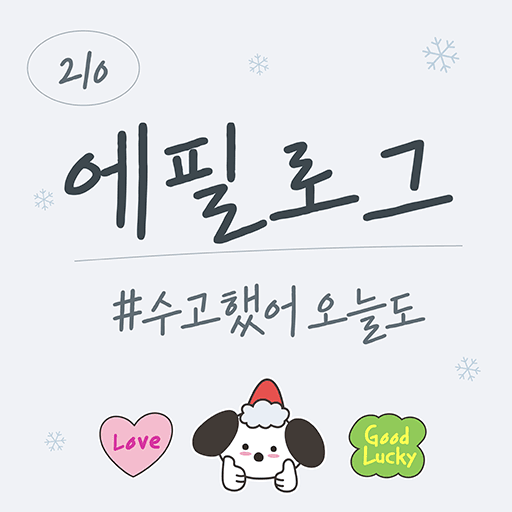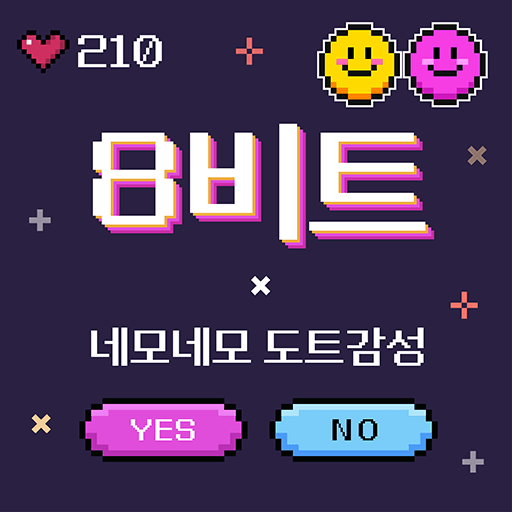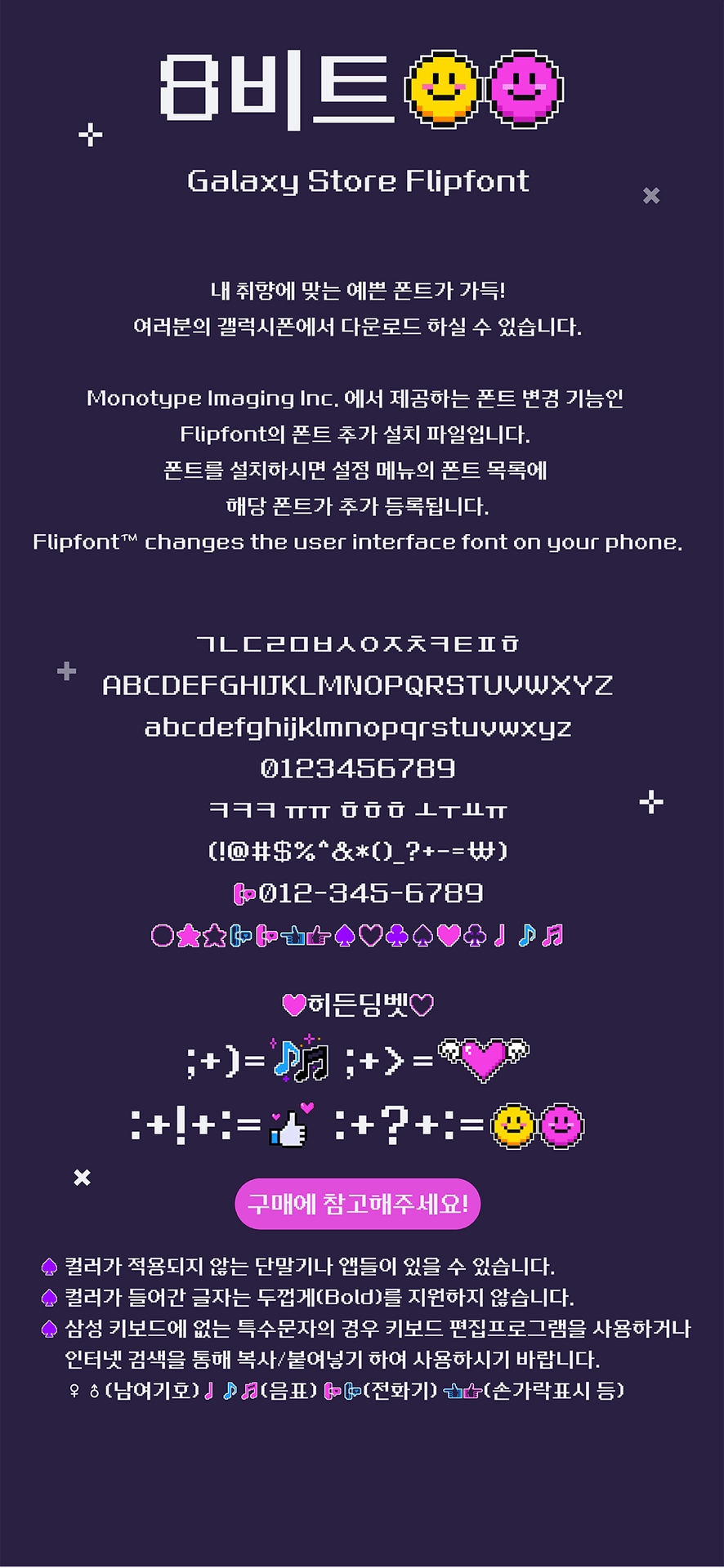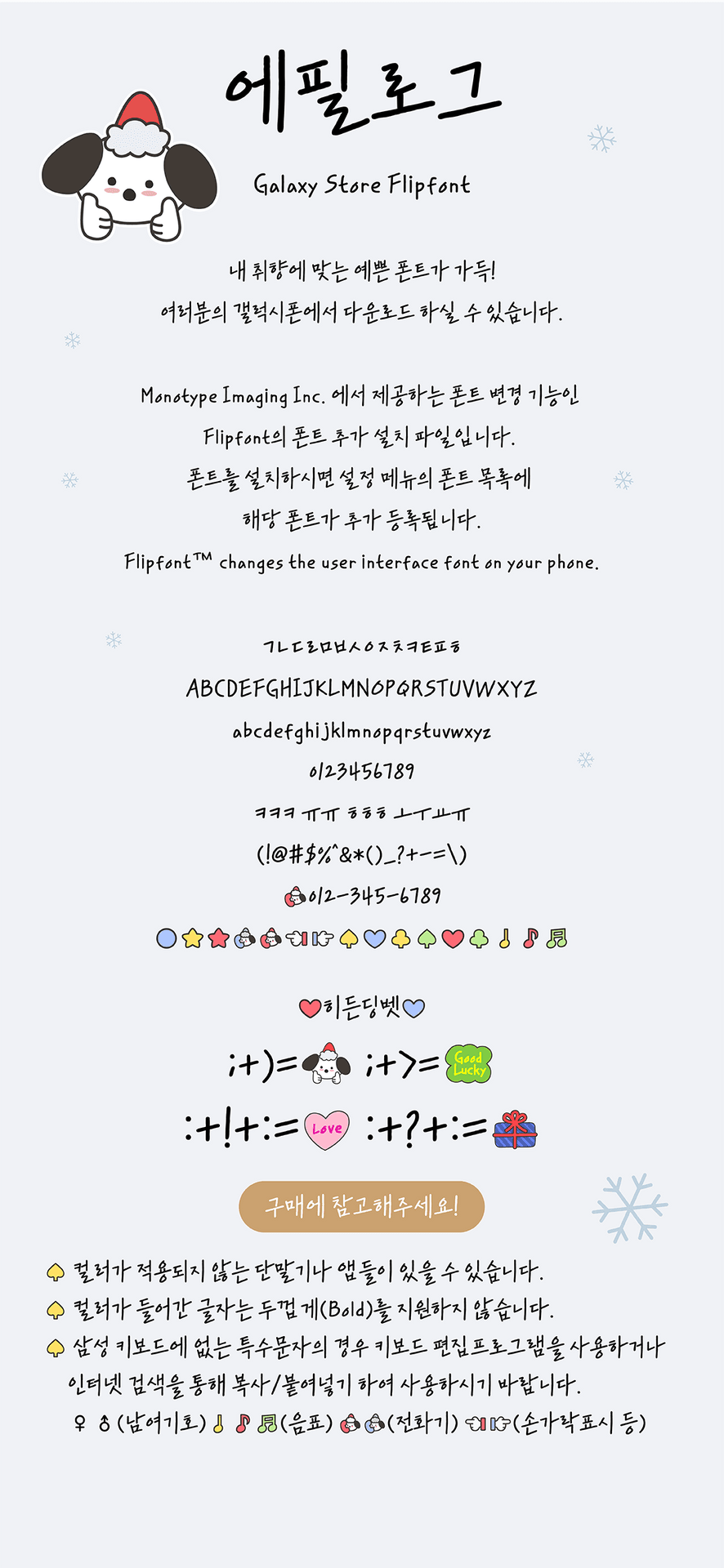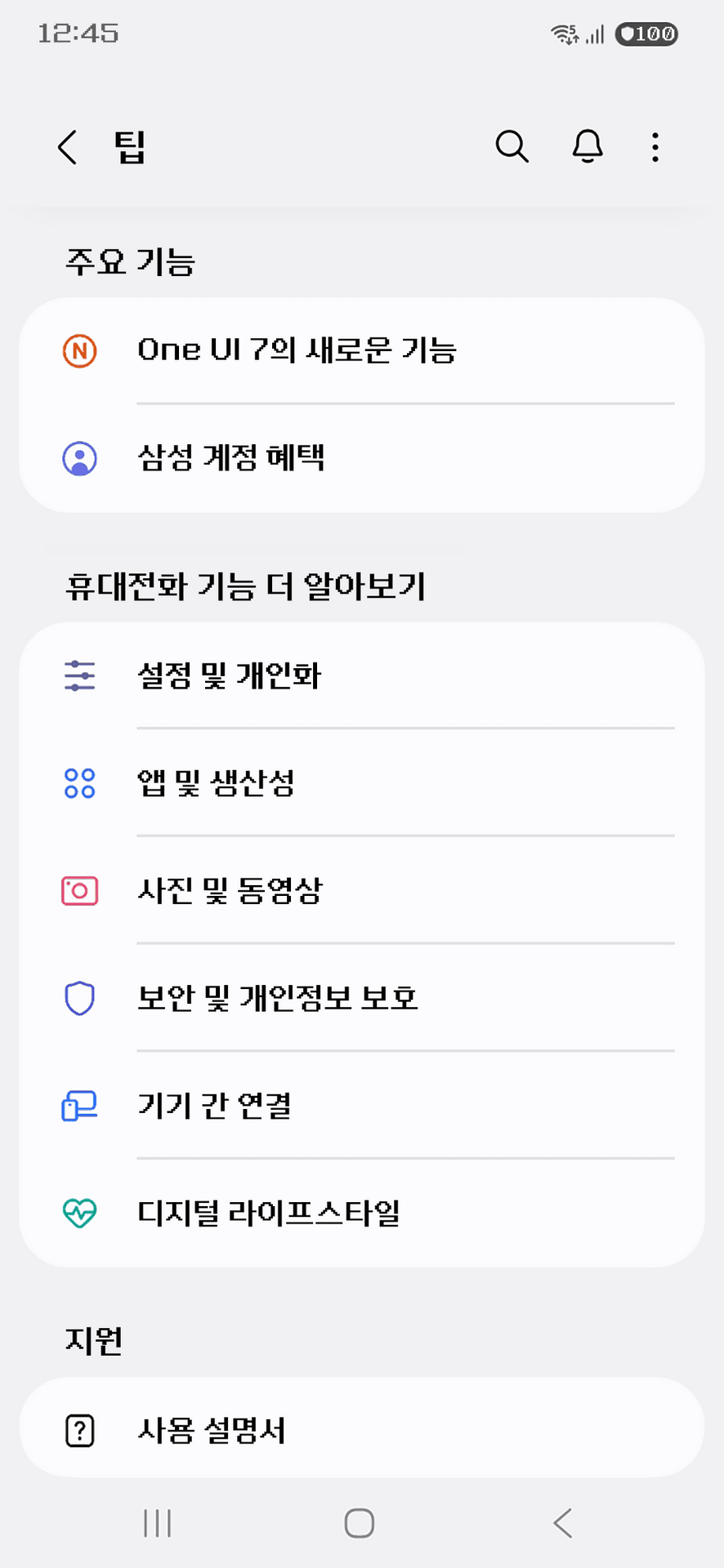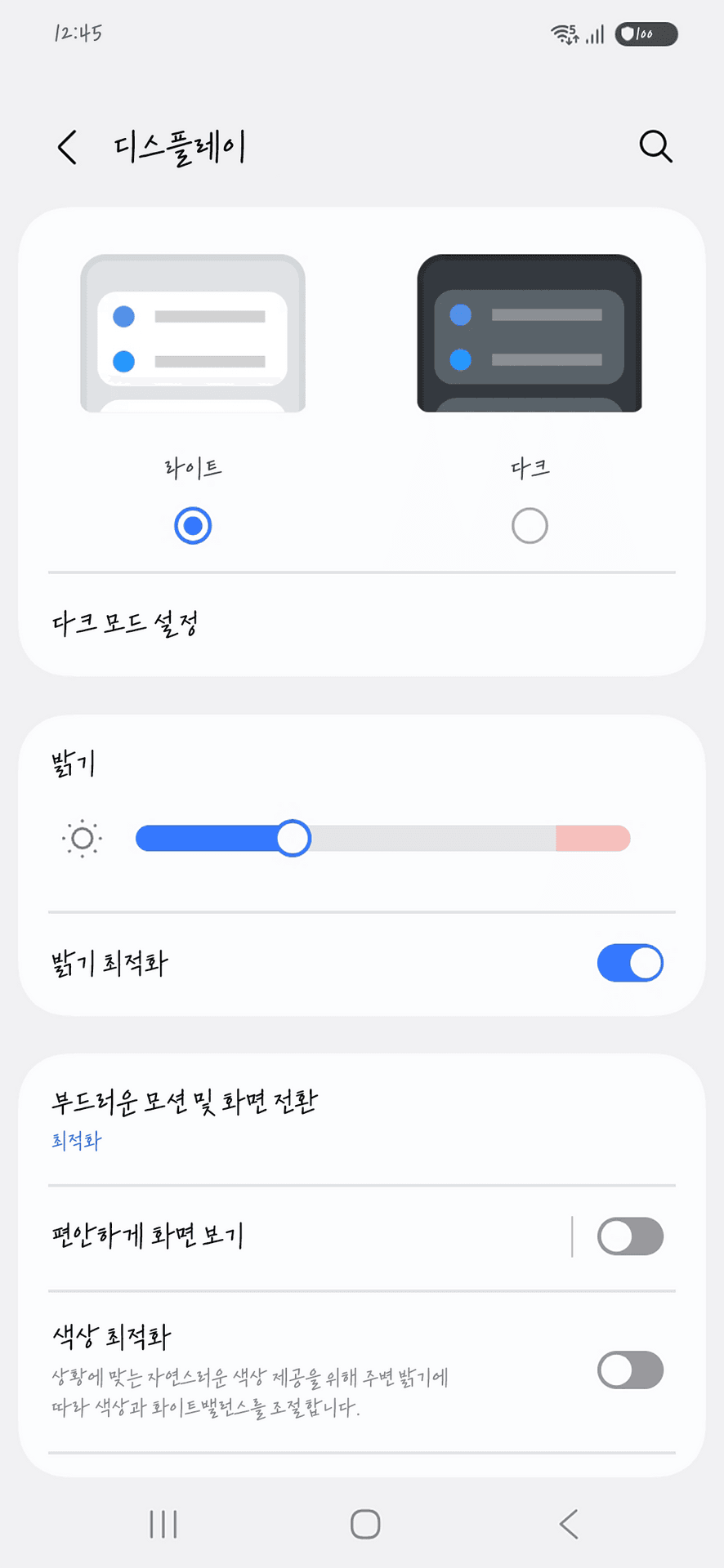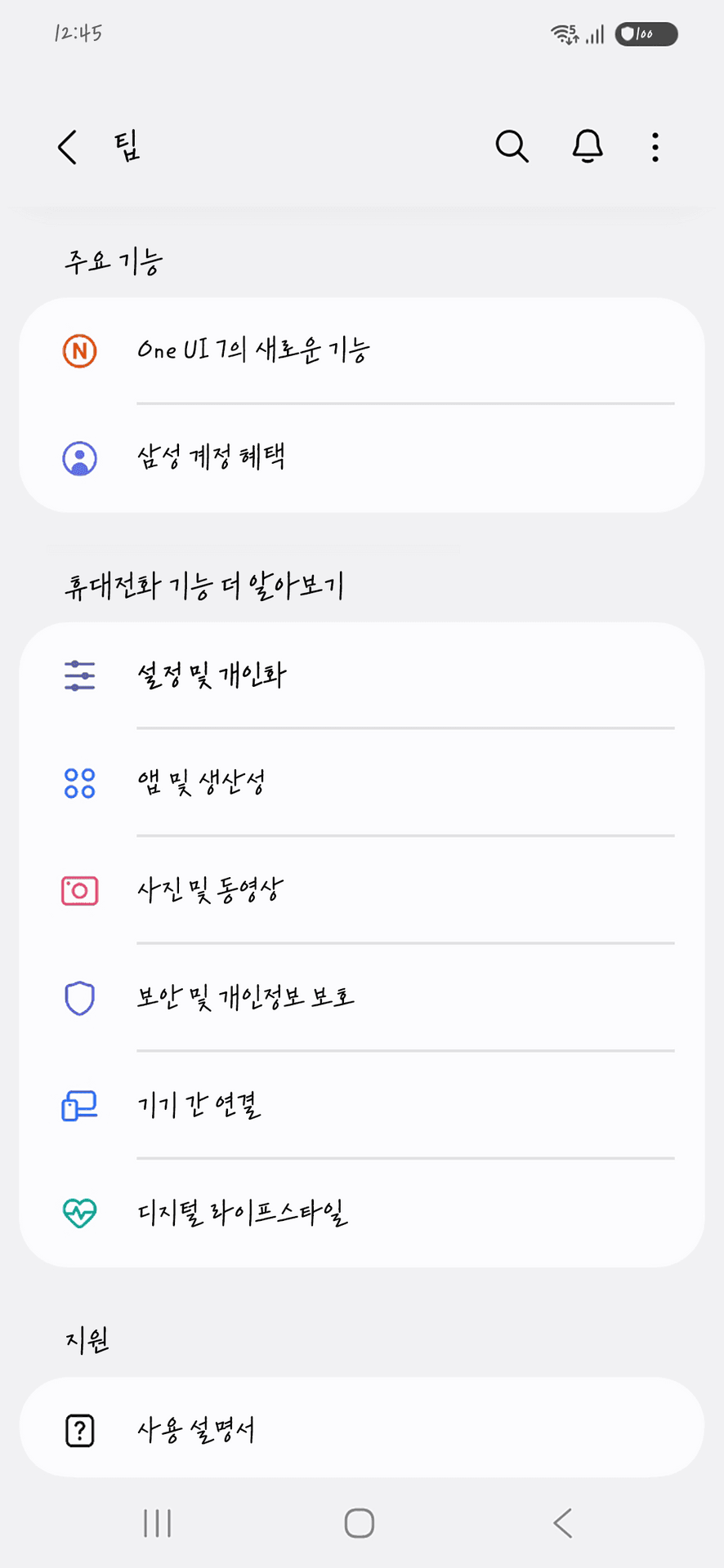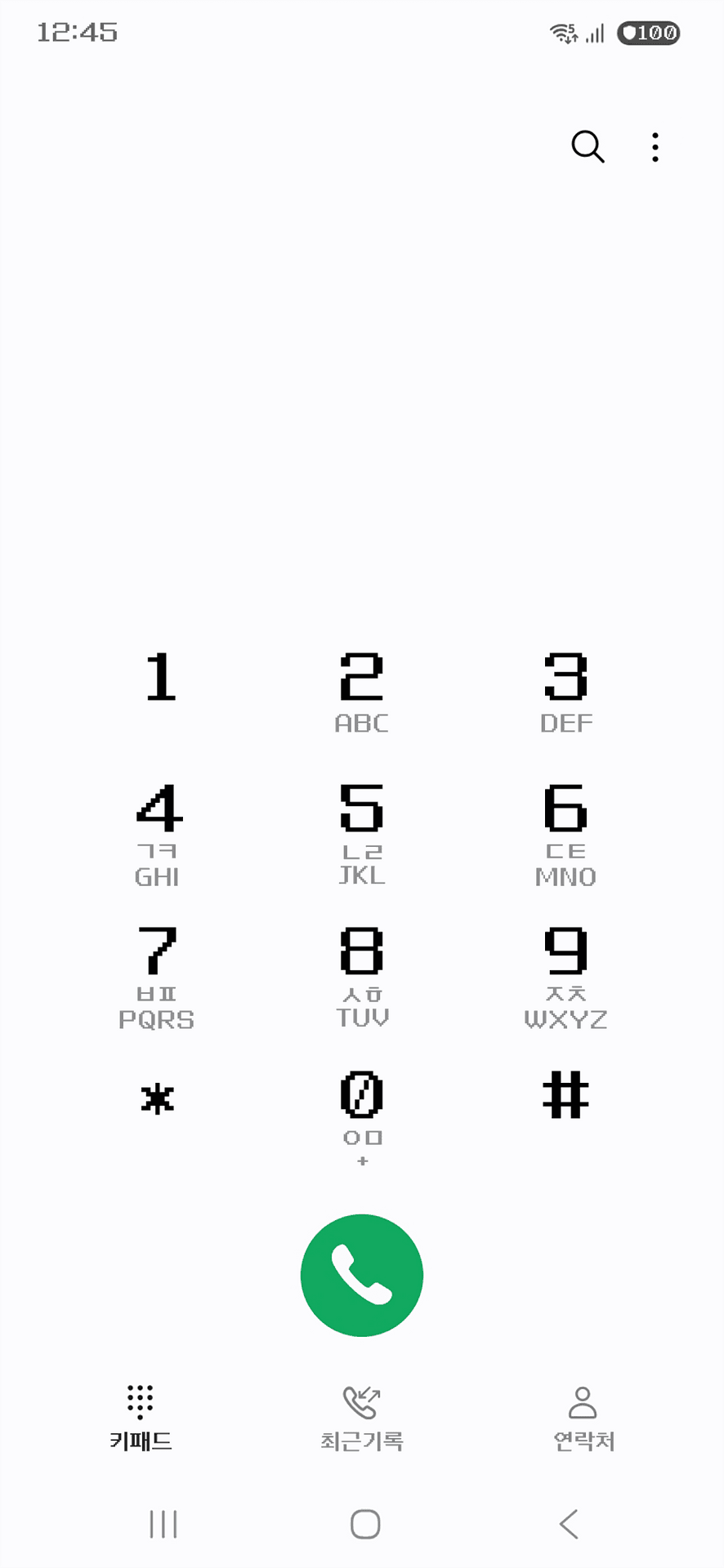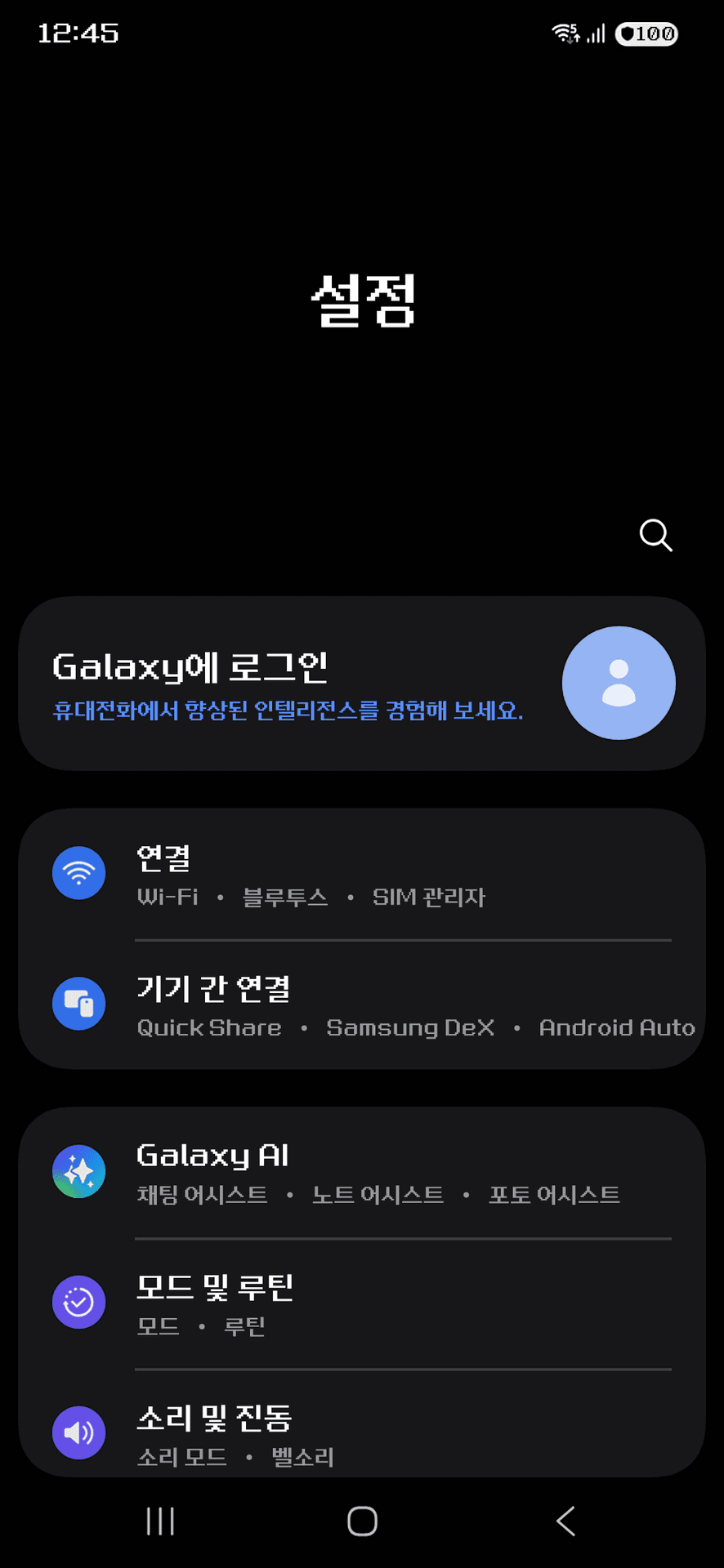
210 에필로그 한국어
겨울의 하얀 감성을 담은 캘리그라피 손글씨 서체입니다. 사인펜으로 쓱 써 내려간 듯한 부드러운 선과 따뜻한 여백이 매력으로, 210이 플립폰트로 처음 선보이는 신규 폰트입니다. 가독성을 높이고 깜찍한 컬러 딩벳을 더해 메시지마다 포근한 겨울 감성을 전합니다.
숨은 딩벳 ;) ;> :!: :?: 를 입력하면 깜찍한 컬러 기호가 나타나요.
따뜻한 캘리그라피 감성의 에필로그 (Epilogue)와 레트로 게임기 감성의 8비트 (8-bit)가 동시에 찾아왔습니다. 두 글꼴 중 어느 쪽이 내 갤럭시에 어울릴까요?
겨울의 하얀 감성을 담은 캘리그라피 손글씨 서체입니다. 사인펜으로 쓱 써 내려간 듯한 부드러운 선과 따뜻한 여백이 매력으로, 210이 플립폰트로 처음 선보이는 신규 폰트입니다. 가독성을 높이고 깜찍한 컬러 딩벳을 더해 메시지마다 포근한 겨울 감성을 전합니다.
숨은 딩벳 ;) ;> :!: :?: 를 입력하면 깜찍한 컬러 기호가 나타나요.
레트로 게임기 화면에서 영감을 받은 픽셀 서체입니다. 마치 내 갤럭시가 추억 속 8비트 게임기로 변하는 듯한 독특한 분위기를 연출하며, 210이 플립폰트로 처음 선보이는 신규 폰트입니다. 가독성을 높이고 컬러 딩벳을 더해 개성 넘치는 화면을 만들어 줍니다.
숨은 딩벳 ;) ;> :!: :?: 를 입력하면 귀여운 픽셀 컬러 기호가 나타나요.
전화 키패드부터 설정 화면, 알림까지. 플립폰트 (Flipfont) 하나로 휴대폰 인터페이스 전체의 분위기가 달라집니다.